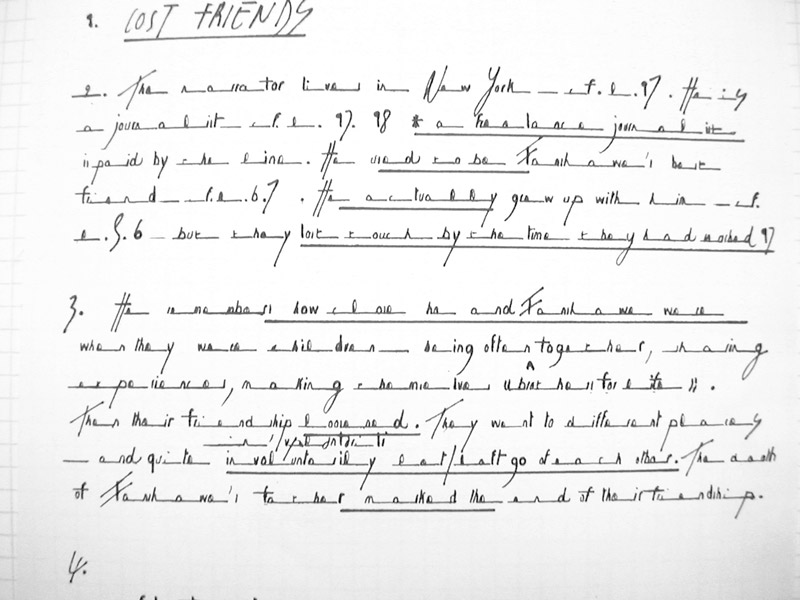
- Subject: calligraphie d'enseignant ou pathologie ?
Il a été question ces temps-ci de l'écriture des enfants à l'école, mais
je crois qu'il y a des sérieuses questions à résoudre côté écriture des
enseignants dans certains cas.
Ci-joint, specimen d'un prof d'anglais, classe de 1re littéraire. Les 35
élèves de la classe ont dû coller ça dans leur cahier.
La prof écrit en s'aidant du bord d'une carte postale, et n'hésite pas
en plus à souligner certains passages...
Comment enseigner, transmettre, quand l'écriture n'a plus valeur de
communication ?
Suis à la fois consternée et furieuse, en plus ce type de graphie me
fait froid dans le dos.
Vous, dont la fille n'est pas dans cette classe, auriez des avis plus
sereins ?